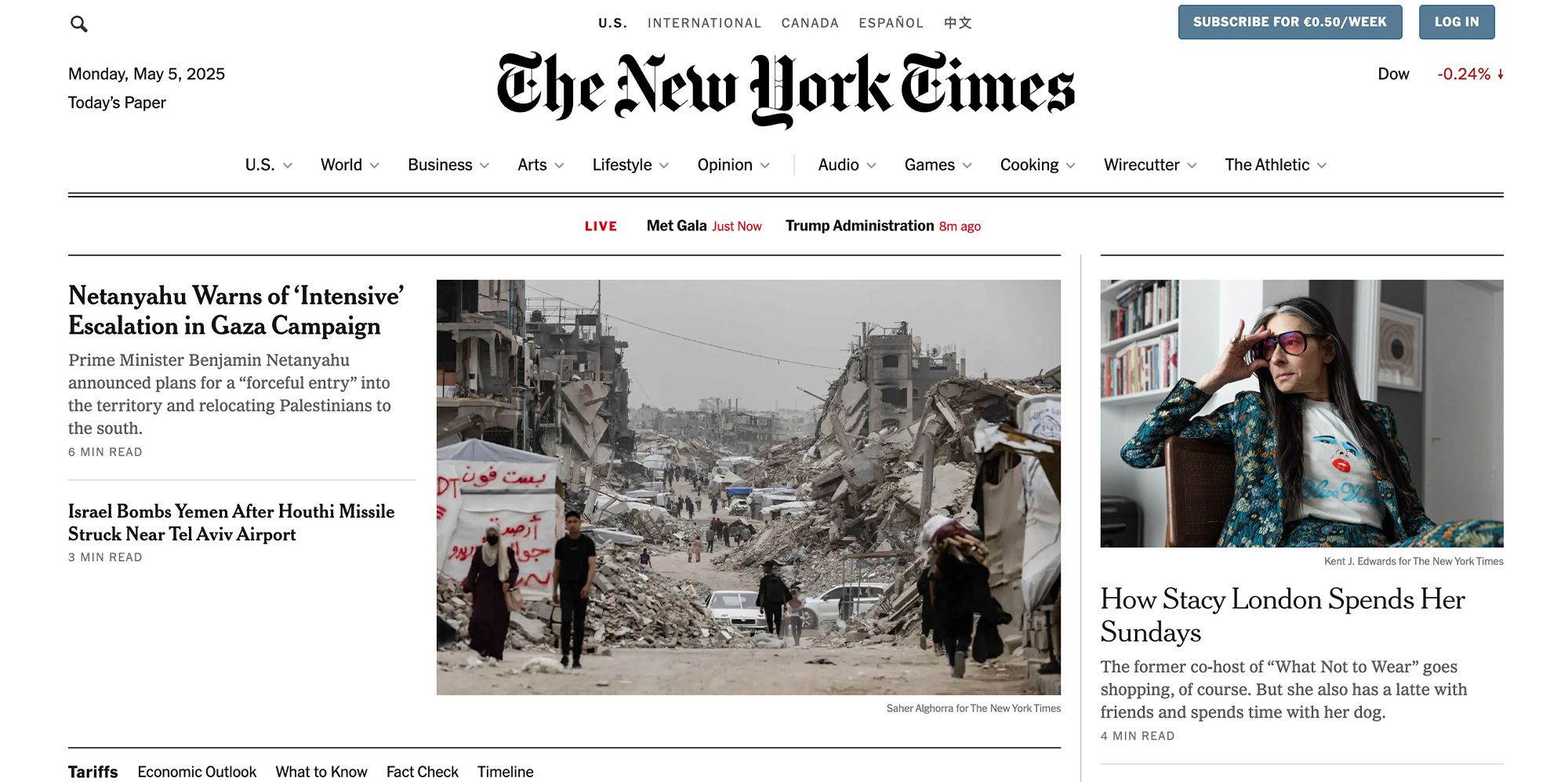
3 marcas que utilizan muy bien la tipografía
Descubre cómo marcas como Burberry, Mailchimp y The New York Times han utilizado la tipografía de forma brillante para definir su identidad.
La tipografía define la personalidad de una marca. Tres ejemplos muestran cómo la coherencia y la creatividad tipográfica impulsan la identidad visual, sirviendo de inspiración para proyectos de diseño.
1. Burberry: elegancia y modernidad tipográfica
En 2018, Burberry renovó su imagen con una identidad tipográfica más sobria y contemporánea, diseñada por Peter Saville. La fuente sans serif, de líneas limpias, transmite sofisticación y minimalismo, reflejando una marca de lujo que se adapta al presente sin perder su herencia británica.
La simplicidad de la tipografía permite que la marca hable con confianza y autoridad. Además, su consistencia en todos los puntos de contacto refuerza el reconocimiento inmediato.
2. Mailchimp: tipografía con personalidad propia
Mailchimp ha logrado destacar en el mundo del marketing digital no solo por sus servicios, sino por su identidad visual juguetona y única. Su uso de la tipografía Cooper Light, con formas redondeadas y amigables, refleja cercanía, creatividad y un enfoque humano.
La tipografía rompe con lo convencional en el sector tech, diferenciándose de competidores más formales. Este gesto refuerza su propuesta de marca accesible y fresca.
3. The New York Times: una tradición tipográfica sólida
La cabecera del New York Times es uno de los ejemplos más icónicos de identidad tipográfica. Su característico logotipo en letra gótica no solo es reconocido mundialmente, sino que proyecta autoridad, historia y credibilidad.
La tipografía actúa como sello de confianza. No ha necesitado grandes cambios porque su fuerza está en la tradición, algo que refuerza los valores del periodismo riguroso.